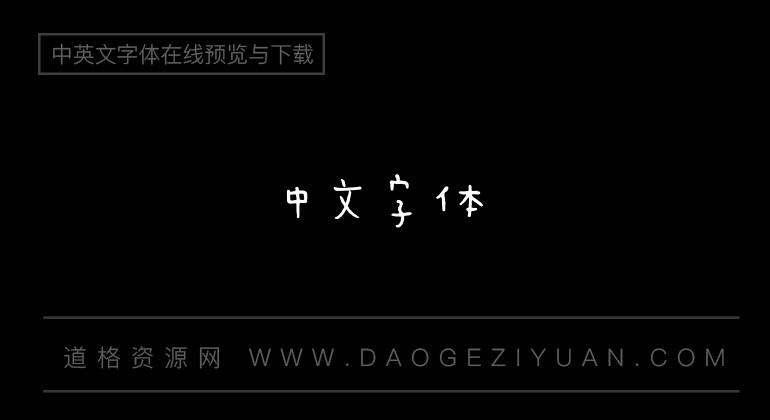
? 玩童体是一款具有温暖、可爱、活泼的字体,它是由著名设计师陈安贤创作的经典款字体。它以圆润的笔画和轻松的节奏营造出一种温暖、安逸的感觉,给人以活泼、可爱的感觉。玩童体也具有良好的可读性,可以用于新闻报道、广告宣传、书籍出版等各种文字应用场景。文件名:naughty-lite-2.ttf
玩童体是一款非常不错的手写艺术字体,具有很好的视觉感,适合于文化类的宣传设计、商业类品牌的广告和产品包装设计以及个性化文字排版等较多场景。